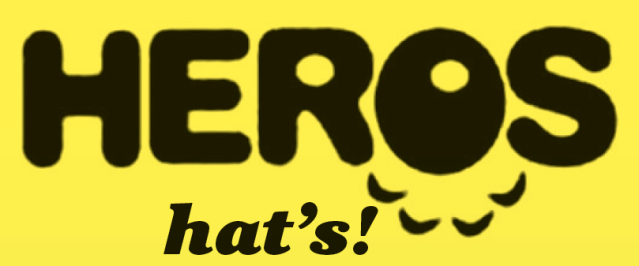
Heros Blur-Schrift
Witzig, daran musste ich auch gleich denken. Vielleicht hat man die einfach auf den Scanner gelegt und dann weiterbearbeitet …? Aber gibt es nicht auch bei Linotype so eine Russisch-Brot-Schrift? Ich schaue gleich mal in das dicke schwarze Buch rein …
Nachtrag: Hmmm, die Linotype Russisch Brot™ ist deutlich ramponierter an den Kanten, die ist es nicht.
Die Helvetica bold rounded kommt (bis auf das R) relativ dicht dran …
Musst Du den Schriftzug nachbauen oder mehr aus der Schrift setzen?
Noch viel näher dran, aber nicht so aufgeschwemmt, sind IMHO folgende Schriften:
* ARAL V2 aus der ARAL CI
* Hero von Fontfabric (*)